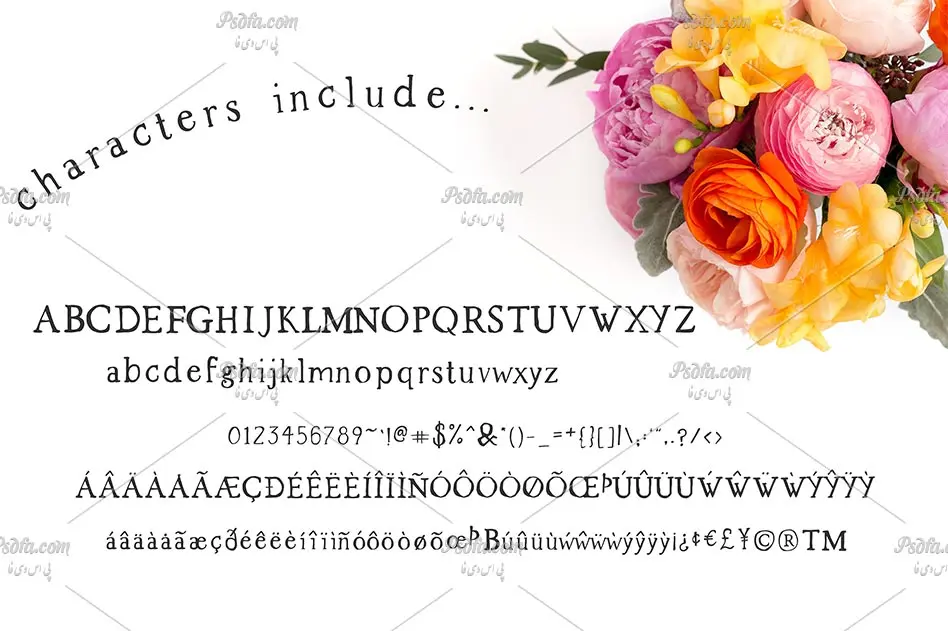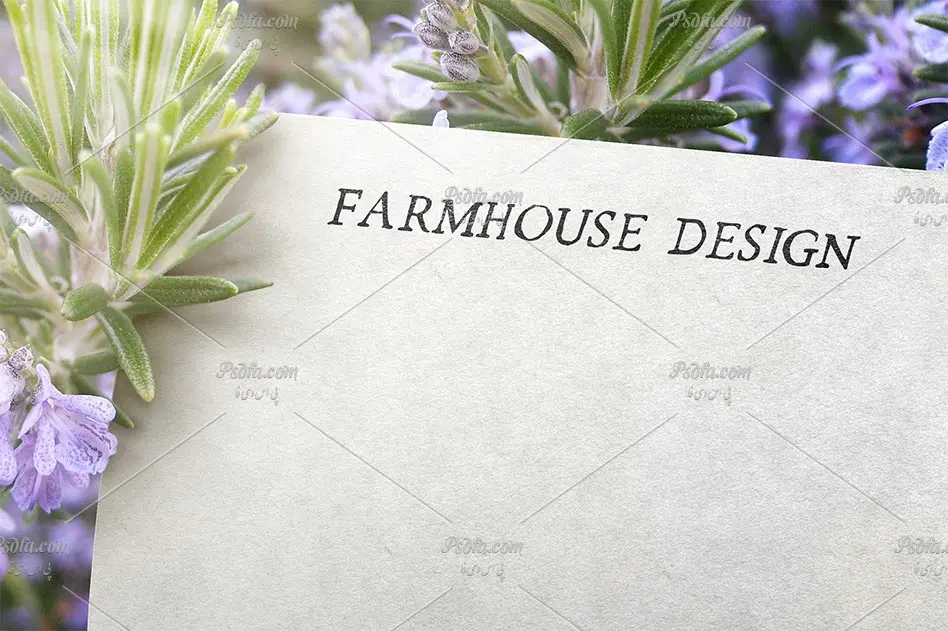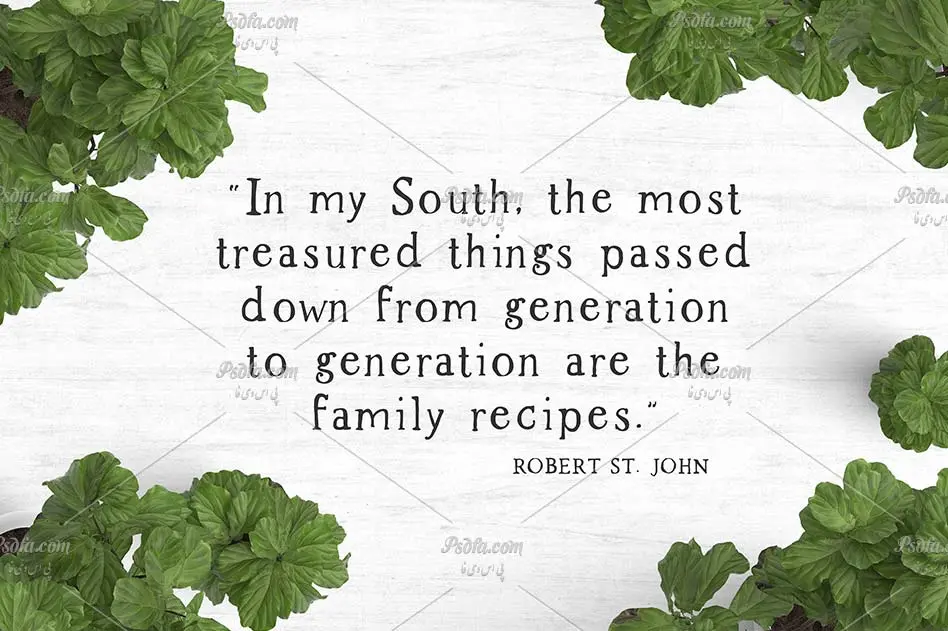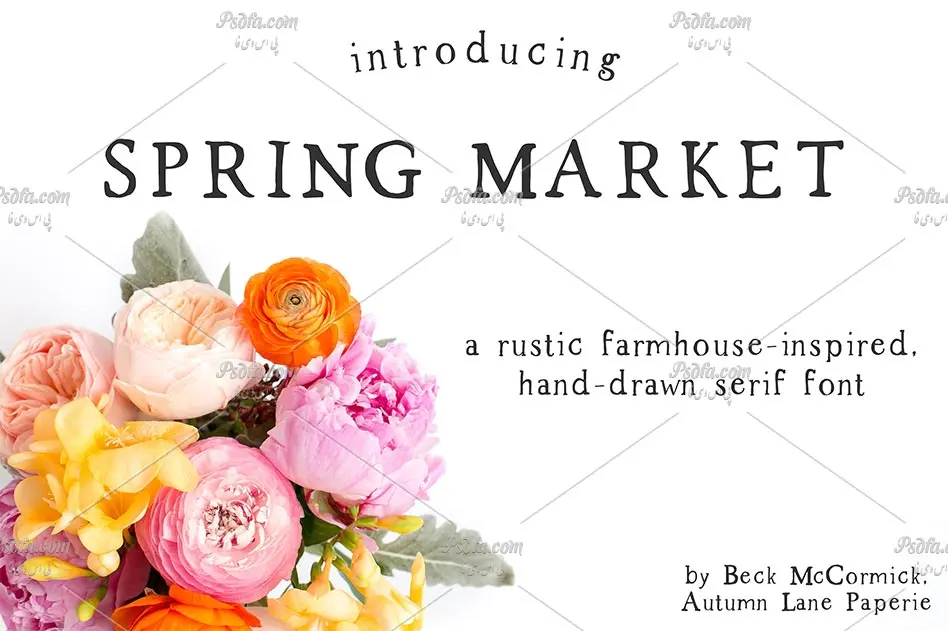
در این مطلب شاهد فونت انگلیسی Spring Market Rustic Font مناسب جهت استفاده در طراحی و گرافیک می باشید. این فونت فوق العاده زیبای انگلیسی که با فرمت otf در سایت قرار داده شده است یکی دیگر از سری فونت های انگلیسی می باشد که از آن می توان در طراحی و گرفیک به خصوص طراحی انواع پوستر با مضامین مختلف استفاده نمود. پس از دانلود فایل و نصب آن در پوشه فونت های سیستم خود می توانید به طور مستقیم از آن در تمام نرم افزارهای گرافیکی و ویرایشگر متن از جمله نرم افزار فتوشاپ ، مجموعه نرم افزار آفیس و … استفاده کنید. پیش نمایش این فونت زیبا و کارکترهای آن را می توانید در تصاویر زیر مشاهده فرمائید.
- نام فونت Spring Market ALP